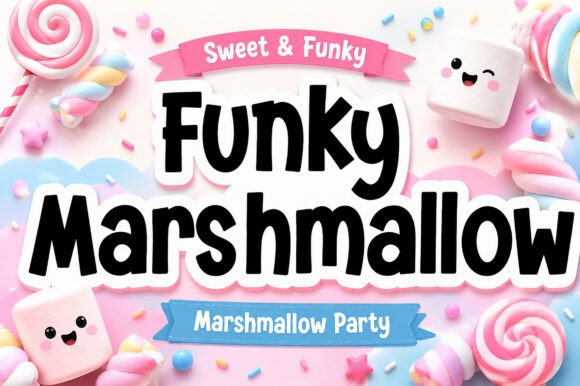
Funky Marshmallow
適切なデザイン要素を見つけるのは難しい場合がありますが、Funky Marshmallowは作品を即座に引き立てる優れたコレクションを提供します。
POD(オンデマンド印刷)製品、結婚式の招待状、またはソーシャルメディアのグラフィックを作成している場合でも、Funky Marshmallowは理想的です。